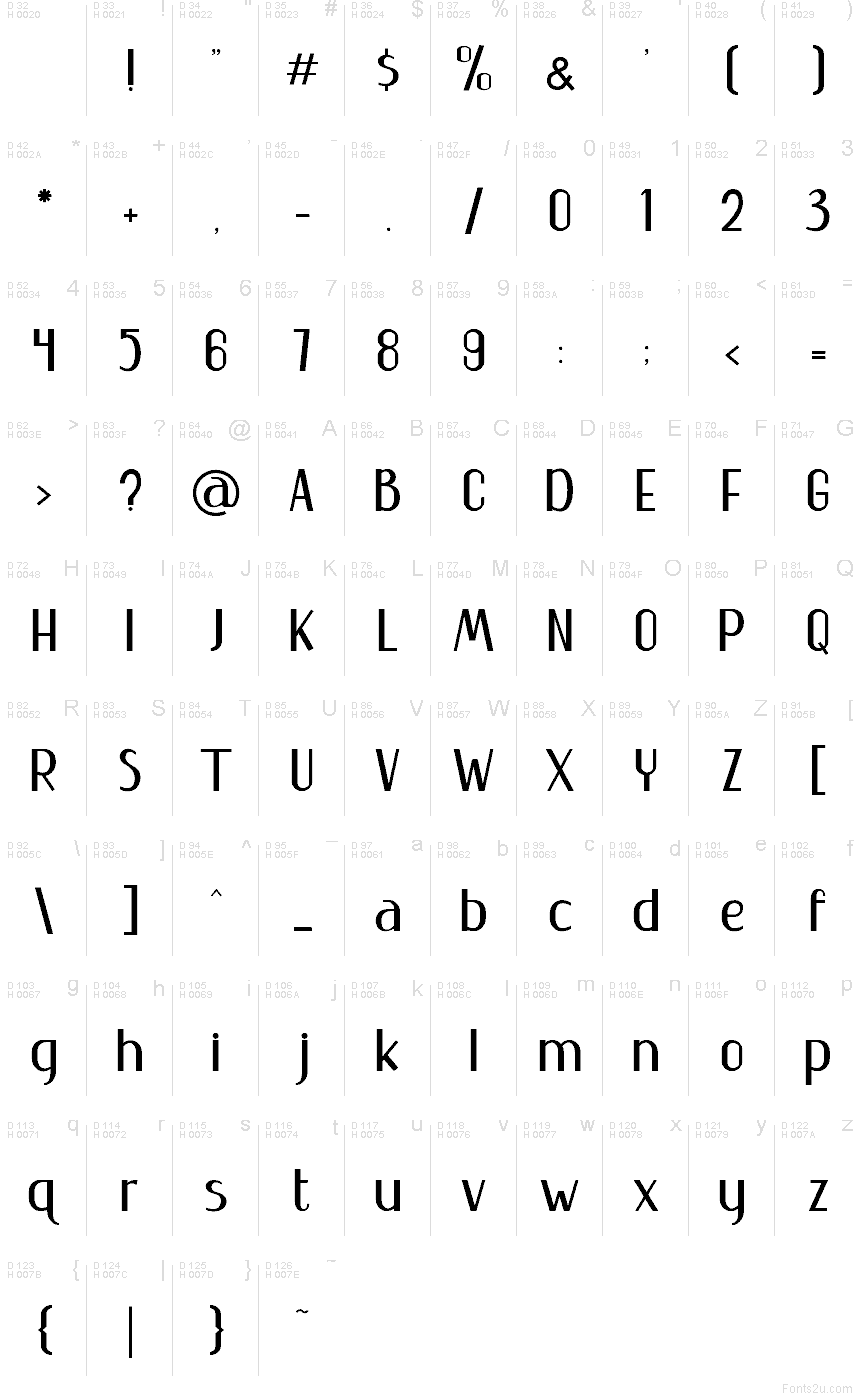
Simply Pleasures Sans
Simply Pleasures Sans od Putracetol Studio je bezplatné komiksové písmo, ktoré definuje uvoľnený rytmus a dlhé vertikálne ťahy. Tie dodávajú písmenám ľahko pretiahnutý, ručne kreslený charakter. Tento opakujúci sa pohyb hore a dole udržuje dizajn živý a neformálny, bez toho, aby pôsobil chaoticky alebo príliš nezvyčajne.
Skvele sa hodí na obálky detských kníh, školské plagáty, obaly na občerstvenie, pohľadnice alebo veselé príspevky na sociálne siete, kde tento „skákavý“ charakter oživí krátke riadky textu. Písmo tiež dodáva nadpisom a jednoduchému brandingu ľudský a priateľský tón – ideálna voľba, keď chcete niečo vrelšie než štandardné bezpätkové písmo, ale menej „presladené“ než klasické skripty.